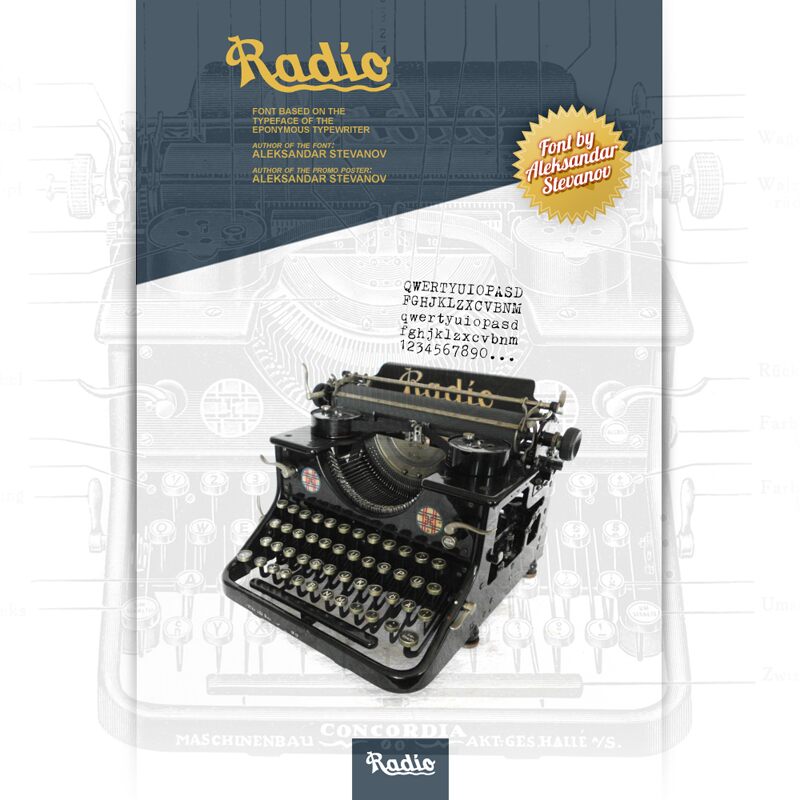
Radio
Radio, zaprojektowany przez Aleksandra Stefanova [wait, keep original designer name: Aleksandar Stevanov], jest darmowym, zniszczonym szeryfowym krojem akcydencyjnym o poszarpanym odcisku starych mechanicznych typów. Nierówne krawędzie, wyszczerbienia i plamy tuszu sprawiają, że każda litera wygląda na fizycznie zużytą. Szerokie szeryfy i nieregularne grubości linii utrzymują solidność form pomimo uszkodzeń.
Najbardziej przekonująco wypada na plakatach muzycznych, gdzie zniszczona faktura druku przywodzi na myśl kserowane ulotki i ręcznie robione druki. Ta sama chropowata powierzchnia pasuje do okładek płyt i niezależnych magazynów zakorzenionych w kulturze punkowej, garażowej lub eksperymentalnej. Tutaj każde wyszczerbienie staje się częścią obrazu.